Dalam desain grafis untuk menggunakan font terkadang juga dilakukan modifikasi untuk menciptakan font yang unik. Modifikasi font bisa diterapkan pada banyak hal seperti logo, poster, dan lainnya. Dalam memodifikasi font untuk kebutuhan desain grafis, penting untuk memperhatikan beberapa tips yang efektif.
Ada beberapa alasan mengapa perlu untuk memodifikasi font dalam merancang desain grafis. Biasanya modifikasi dilakukan agar tampil beda dari font yang sudah ada sehingga lebih menarik. Selain itu modifikasi font juga dilakukan untuk menghindari copyright.
Tidak semua font bisa digunakan secara gratis, untuk itu penting melakukan modifikasi untuk membuat font tampil beda. Dalam memodifikasi font berguna untuk meningkatkan gaya tarik visual desain. Untuk memodifikasi font dengan efektif, simak pembahasan ini yang akan menjelaskan tips dalam memodifikasi font dalam desain grafis.
TIPS MODIFIKASI FONT DALAM DESAIN GRAFIS
Dalam menciptakan desain grafis yang menarik perhatian penting untuk bisa modifikasi font yang unik. Dengan melakukan modifikasi font ini akan membantu untuk menyampaikan pesan lebih efektif. Berikut beberapa tips modifikasi font dalam desain grafis:
Pilih Font yang Sesuai
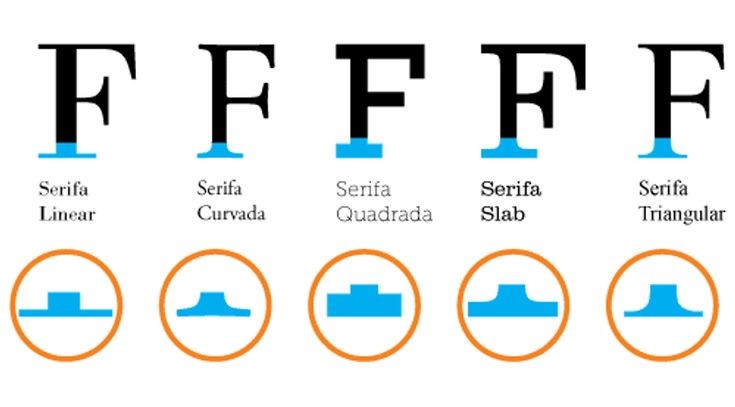
Dalam memodifikasi font penting untuk memilih terlebih dahulu. Pilih jenis font yang ingin dimodifikasi sesuaikan dengan kebutuhan dan tujuan desain. Meski masih akan dimodifikasikan lagi penting untuk memilih jenis font yang telat sesuai dengan tema desain.
Memilih font yang sesuai dengan kebutuhan akan memudahkan untuk dimodifikasi ke dalam bentuk huruf yang menarik. Ketika memilih font pertimbangkan faktor keterbacaan, sehingga ketika dimodifikasi huruf akan mudah untuk dibaca. Pertimbangkan juga gaya font yang dipilih apakah bisa menciptakan konsistensi dengan merek atau konsep desain.
Memahami Anatomi Font
Ketika akan memodifikasi font penting untuk memahami terlebih dahulu anatomi font. Ini akan membantu memahami bagian-bagian dalam huruf yang sekiranya bisa dimodifikasi dengan menarik. Sebuah huruf memiliki banyak sekali bagian, seperti serius, x-height, ascender dan descenders.
Biasanya modifikasi font dimulai dari menentukan bagian dari font mana yang bisa diubah. Memodifikasi bagian-bagian font akan membantu untuk menciptakan font baru yang unik. Terkadang ada bagian-bagian tertentu saja yang dimodifikasi untuk menciptakan keseluruhan huruf terlihat konsisten.
Perhatikan Proporsi
Dalam memodifikasi huruf perhatian pula proporsinya. Ketika ada perubahan ketebalan dan ukuran perhatikan antar huruf memiliki proporsi yang pas. Ini penting untuk menjaga tampilan font tetap seimbang dan nyaman untuk dilihat.
Biasanya dalam modifikasi font perubahan font bisa bervariasi, entah itu menambahkan serif, memotong huruf, atau mengubah ketebalan huruf. Untuk itu penting memastikan dalam modifikasi huruf tetap memiliki proporsi tampilan huruf yang harmonis dan seimbang antara huruf.
Ketahui Batas-batasnya
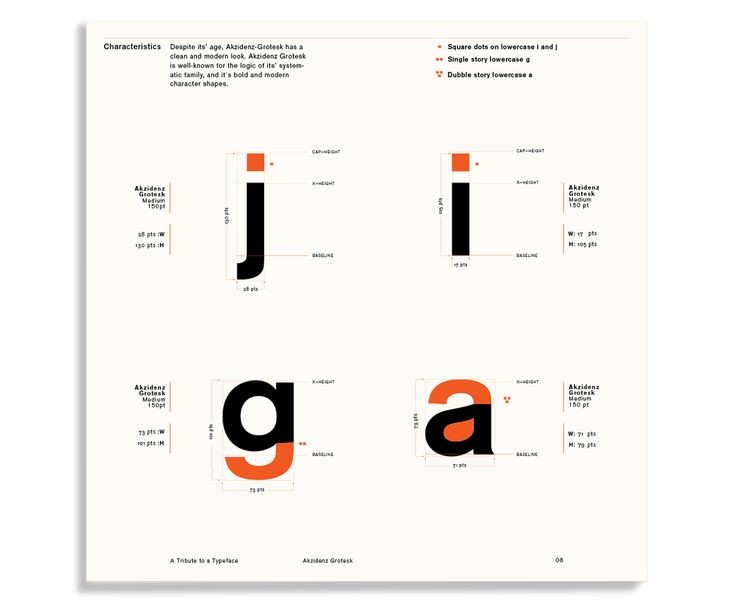
Penting juga memerhatikan batas-batas dalam memodifikasi font, hal ini karena modifikasi yang berlebihan membuat huruf jadi kurang jelas. Modifikasi huruf secukupnya agar bentuknya tetap sederhana dan bisa terbaca dengan jelas. Dalam memodifikasi huruf jangan terlalu berlebihan atau dipaksakan agar desain huruf tidak berantakan.
Perlu dipahami jika memodifikasi font tidak sama dengan membuat huruf baru. Jangan terlalu berlebihan dalam memodifikasi huruf agar tidak menghilangkan karakter asli font. Hal ini karena modifikasi berlebihan bisa membuat font kehilangan identitasnya.
Gunakan Tool yang Tepat
Untuk memodifikasi font bisa menggunakan software desain grafis seperti coreldraw atau illustrator. Gunakan tools yang tepat untuk mengatur jarak huruf, ketebalan, menambahkan dekorasi hingga memotong huruf.
Manfaatkan beragam tools dalam aplikasi digital untuk memodifikasi font dengan menarik. Tidak hanya mengatur bentuk dan dekorasi huruf, manfaatkan juga untuk mengatur jarak huruf, spasi dan ukurannya dengan presisi dan nyaman dilihat.
Jaga Konsistensi
Dalam modifikasi font untuk kebutuhan desain grafis perhatikan juga untuk menjaga konsistensi. Setiap huruf harus dimodifikasi pada bagian yang sama untuk menciptakan konsistensi. Hindari untuk memodifikasi pada bagian yang berbeda-beda karena bisa membuat font tidak memiliki keseimbangan visual.
Gaya setiap huruf yang dimodifikasi harus menciptakan konsistensi visual secara keseluruhan. Hindari penggunaan variasi berlebihan dan berbeda-beda agar font tidak terlihat bertentangan. Ketika gaya setiap huruf berbeda ini bisa membuat desain tidak teratur dan tidak terlihat profesional.
Perhatikan Keterbacaan
Dalam modifikasi huruf penting juga untuk memerhatikan agar modifikasi yang dilakukan dapat menjaga keterbacaan tulisan. Pastikan sentuhan kreatif atau modifikasi font tetap mudah untuk dibaca dan dikenali hurufnya. Meskipun terkadang ingin dibuat seunik dan semenarik mungkin, pastikan desainnya tetap mudah untuk dibaca.
Untuk menciptakan desain grafis semakin menarik, melakukan modifikasi font bisa membuat desain semakin menarik. Font yang digunakan dalam sebuah desain bisa membosankan, maka dari itu modifikasi diperlukan agar font tampil beda. Namun dalam memodifikasi font penting untuk memperhatikan beberapa hal agar modifikasi font efektif dan menarik. Pastikan modifikasi font menciptakan bentuk yang menarik, konsistensi huruf, dan keterbacaan yang jelas. Hal ini huruf yang dimodifikasi mudah untuk menyampaikan pesan dengan efektif.